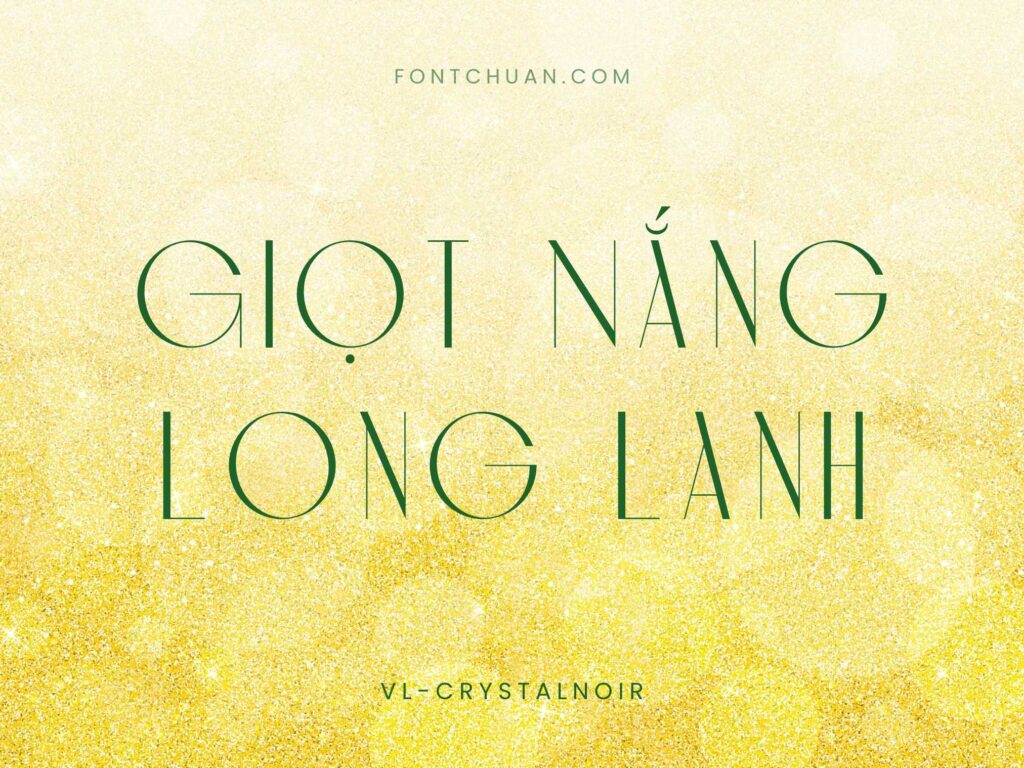
Font VL Crystal Noir Việt Hóa
Tác giả Font: Calamar Studio
Việt hóa bởi: Font Việt Linh
VL-Crystal-Noir là một phông chữ sans-serif thanh lịch, được thiết kế bởi Calamar Studio. Phông chữ này mang lại cảm giác sang trọng và hiện đại, phù hợp cho các thiết kế như tiêu đề, logo, thiệp mời và nhiều ứng dụng khác. VL-Crystal-Noir đã được Việt hóa bởi Việt Linh, hỗ trợ đầy đủ các ký tự tiếng Việt, giúp người dùng dễ dàng sử dụng trong các dự án sáng tạo. Phông chữ này được thành viên Font Chuẩn sưu tầm và đăng tải nhằm phục vụ nhu cầu thiết kế đa dạng.
Với thiết kế tinh tế và rõ ràng, VL-Crystal-Noir phù hợp cho các ứng dụng như tiêu đề, văn bản dài, thiết kế logo và các ấn phẩm in ấn. Trong lĩnh vực sự kiện, phông chữ này có thể được sử dụng trong các dịp như lễ hội, thiệp cưới và các sự kiện văn hóa. Ngoài ra, VL-Crystal-Noir cũng thích hợp cho các ngành nghề như quảng cáo, giáo dục và công nghệ.